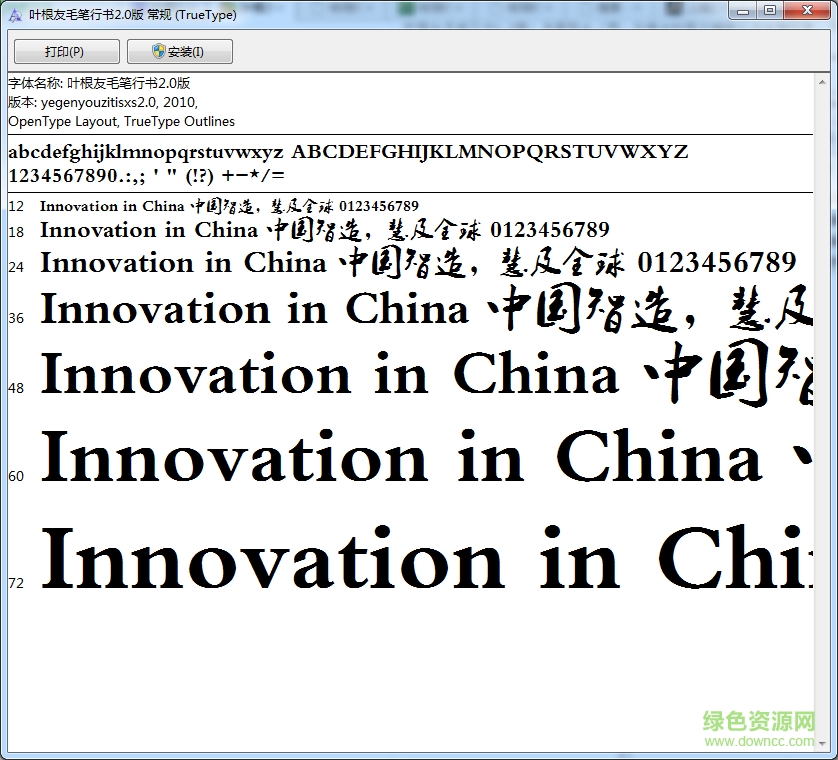
葉根友毛筆行書2.0版是一款全新的葉根友字體,字體簡(jiǎn)潔手寫體極具個(gè)性,漢字?jǐn)?shù)字英文輸入都可快速顯示,使用領(lǐng)域廣泛深受廣大用戶喜愛??靵砭G色資源網(wǎng)下載體驗(yàn)吧!
葉根友毛筆行書2.0版是一款具有獨(dú)特風(fēng)格的字體字體,筆畫風(fēng)格大氣流暢,書寫自然,是一種純手寫字體的經(jīng)典之作,因此它也是葉根友字體系列最受歡迎的字體之一。筆意取自米芾書法風(fēng)格,大氣而又自然流暢是這款字體的主要風(fēng)格。廣泛應(yīng)用于社會(huì)各界的廣告招牌、影視作品以及游戲應(yīng)用等。需要的可以來下載。